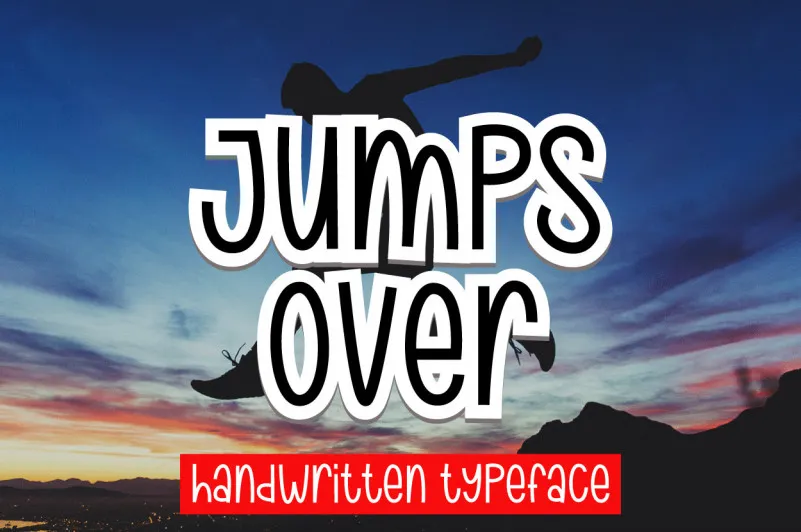
Jumps Over Font – Download Grátis
Descobrir uma nova fonte pode ser uma verdadeira aventura na literatura digital. Introduzimos a “Jumps Over Font”, uma elegante tipografia sans-serif que traz leveza e simplicidade aos seus projetos digitais. Esse tipo foi criado por sugiharto1790, um designer talentoso que nos oferece uma fonte única com seu próprio estilo. Ideal para criar design gráfico moderno, a “Jumps Over Font” é perfeita para ambientes onde precisamos de uma aparência limpa e minimalista. Seja você um profissional ou apenas um amante do design digital, esta fonte traz funcionalidade e beleza em uma só peça. A qualidade desta tipografia sans-serif torna-a ideal para o uso em sites, gráficos publicitários, materiais de marketing ou qualquer projeto que exija uma aparência minimalista e moderna. Descubra a diferença que essa fonte pode fazer em seus projetos digitais, unindo elegância com simplicidade. Instale já e experimente como é ser um designer no seu próprio estilo.
Designer: sugiharto1790